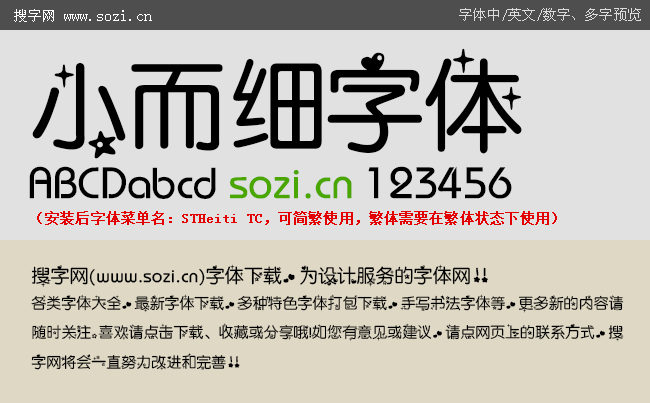
小而細(xì)字體
搜字網(wǎng)給大家提供一款小而細(xì)字體手機(jī)中文字體下載。這款手機(jī)字體是以圓體字體為原形,筆畫間嵌入了可愛(ài)的卡通圖案。在具備圓字體清晰端正的風(fēng)格同時(shí),卡通味也特別濃,是一款非?蓯(ài)的卡通字體,特別適合喜歡手機(jī)字體個(gè)性一些的朋友在手機(jī)上安裝使用。